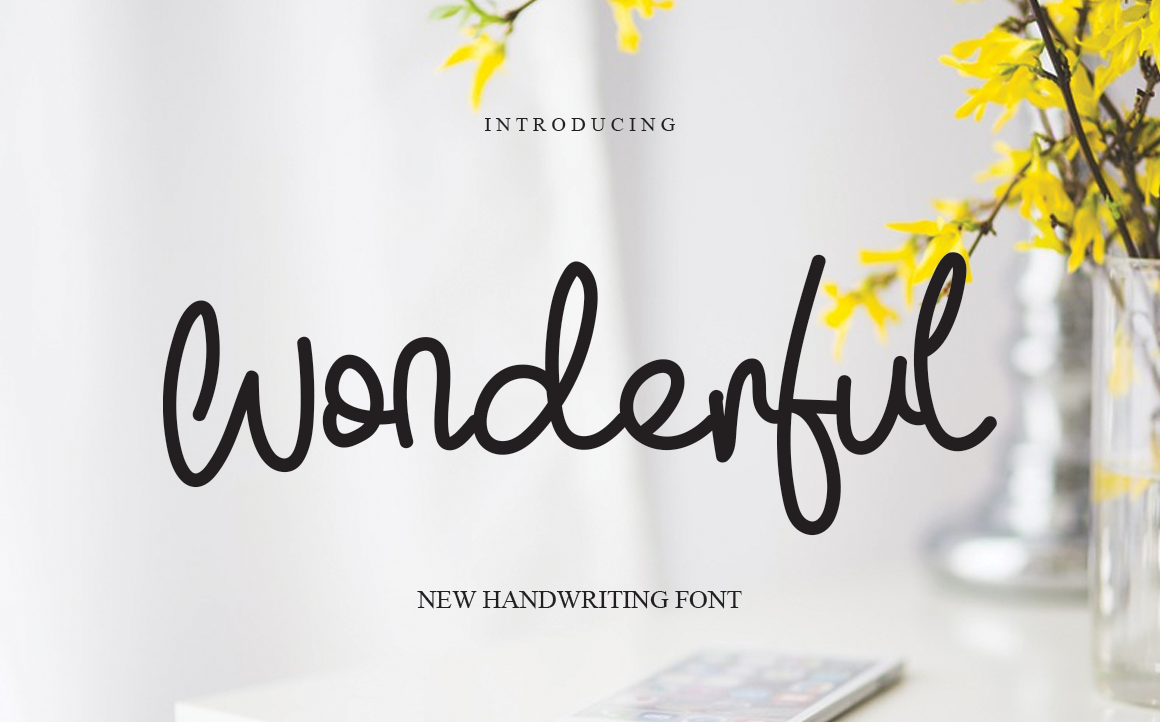
Wonderful Font – Download Grátis
A fonte “Wonderful Font” é uma opção perfeita para quem busca personalidade no seu design. Trata-se de uma fonte feita à mão livre que incorpora traços criativos e alegres, ideal tanto para as redes sociais como para projetos de calligrafia DIY. Seja você um artesão ou apenas alguém buscando decorar seus trabalhos com estilo, esta fonte transformará suas ideias únicas em obras verdadeiramente artísticas. Com “Wonderful Font”, qualquer projeto pode ser elevado a um novo patamar, adicionando aquela pitada especial de originalidade e criatividade que tanto valorizamos no design contemporâneo. Que tal experimentar essa fonte elegante que combina sofisticação com alegria?